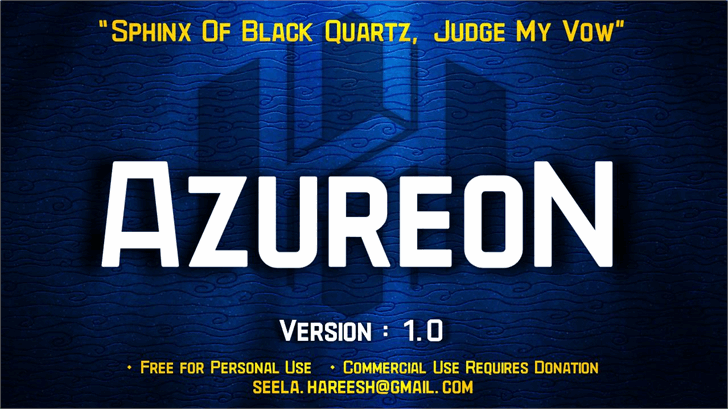
AzureoN Font – Download Grátis
A fonte AzureoN é uma escolha excepcional para qualquer projeto que deseje imprimir algo chamativo e único. Desenvolvida por Hareesh Seela, esta fonte para ambientes de exibição é perfeita para criar um efeito impactante em sua próxima impressão. Lançada em 19 de junho de 2017, a AzureoN oferece uma variedade impressionante de caracteres, projetados para fornecer uma experiência visual vibrante e sofisticada. Com seu design contemporâneo e forte, é perfeito para títulos e headlines de qualquer mídia impressa, garantindo que seu conteúdo seja notado e lembrado por sua audiência. Seja para um poster de jornal ou o logotipo de uma marca em alta, a AzureoN está aqui para fornecer a personalidade necessária para destacar seu design.